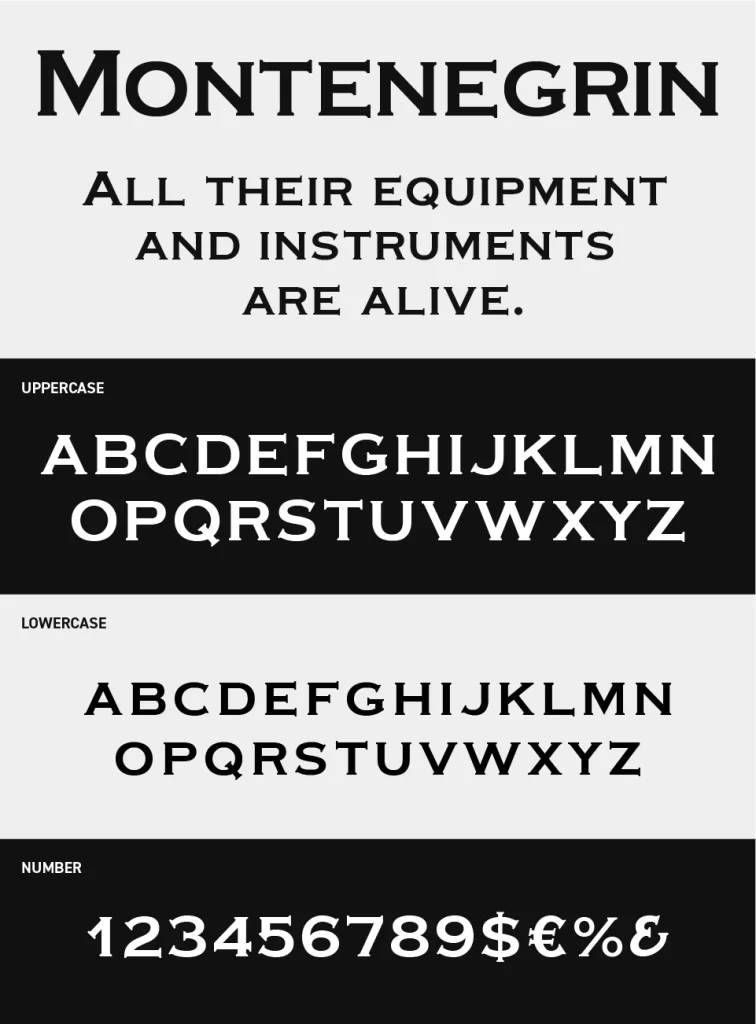
Montenegrin Gothic One Fontは、クラシカルなセリフ体をベースに、鋭く伸びるセリフや細かな装飾を取り入れた気品あるディスプレイフォントです。
文字の端に施された繊細なアクセントが独特のリズムを生み出し、伝統的な書体でありながら華やかさも感じられます。歴史や格式を思わせる雰囲気と、装飾的な美しさを兼ね備えたフォントです。
高級レストランやホテル、ワインラベル、クラシック音楽のポスター、歴史やファンタジーをテーマにしたデザインなどにぴったりです。見出しとして使用することで上品な存在感を演出でき、格式あるブランドイメージや物語性を引き立てるアクセントとして活躍してくれるフォントです。